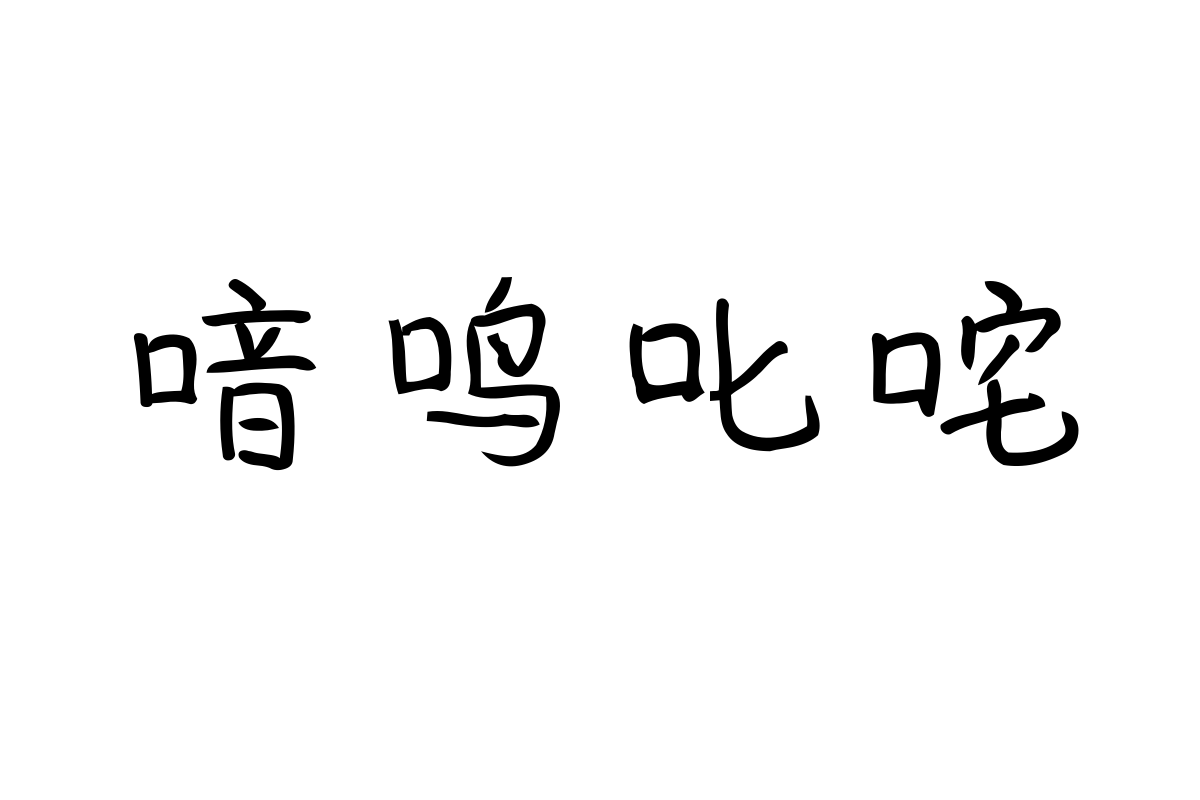
蝉羽冰糖葫芦是一款具有中国传统风格的字体,它的特点是笔画流畅、结构紧凑,给人一种优雅而古朴的感觉。这款字体的笔画粗细适中,既有力度又不失柔美,非常适合用于制作文字广告、宣传海报等需要突出传统文化气息的设计作品。同时,蝉羽冰糖葫芦也适合用于制作各种与中国文化相关的产品包装设计,如茶叶包装、丝绸制品等,能够很好地传达出产品的文化内涵和艺术价值。